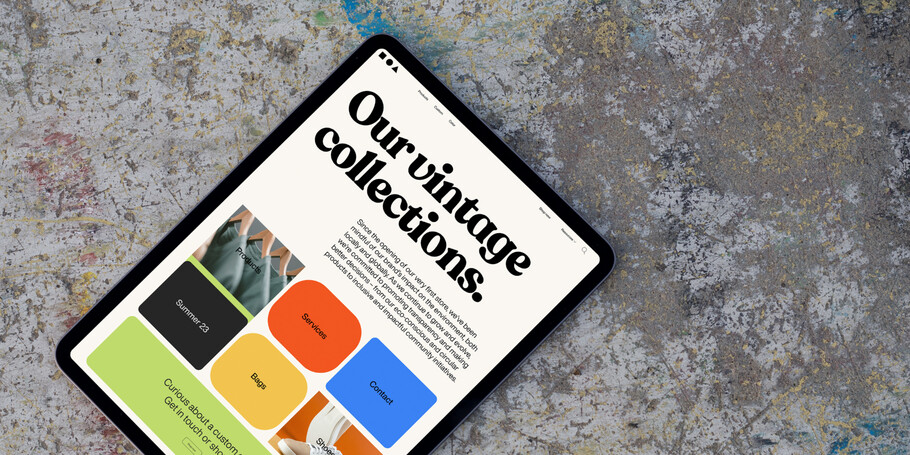
5 manières de renforcer la présence digitale de votre marque.
Vos polices de marque peuvent-elles passer en toute simplicité de votre magasin à un environnement Web ? Vos polices de caractères sont-elles lisibles dans une application ? Qu’en est-il des publicités ou des bannières numériques ?
Et des nouveaux environnements, tels que le métavers ? Qu’il s’agisse d’une simple page Web, d’une bannière publicitaire numérique, d’une application, d’une expérience en réalité virtuelle ou encore d’un nouveau jeu dans une arène virtuelle… Force est de constater qu’assurer la présence omni-canal et la transformation numérique d’une marque de manière cohérente sur toutes les plateformes, cela n’est pas une mince affaire.
De nos jours, les consommateurs naviguent à travers les écrans, passent du petit au grand et inversement. Les marques doivent impérativement suivre le mouvement. Et le choix des polices de caractères joue un rôle majeur. Si une marque veut maintenir un niveau de confiance élevé et créer une expérience client positive, il lui faut une présence cohérente sur tous ses points de contact.
La prochaine fois que vous vous retrouvez sur un projet de design pour le monde moderne, assurez-vous que vos polices de caractères sont à la hauteur de l’ère numérique. Utilisez cette check-list pratique pour ne rater aucun des éléments à vérifier.
1. La lisibilité
Si un designer trouve une police qui est parfaitement lisible sur un appareil, il faut savoir que celle-ci n’aura pas forcément la même clarté sur un autre. Agaçant ? Oui. Peut-on y remédier ? Tout à fait. Certaines pratiques peuvent entraîner un certain flou, une imprécision, voire une méfiance à l’égard d’une marque. C’est notamment le cas si vous utilisez une police native d’une application ou bien si vous ajustez l’espacement, caractère par caractère, jusqu’à ce que ce soit parfaitement lisible dans votre application de design. Les consommateurs doivent pouvoir lire facilement vos polices de caractères sur tous types de supports numériques, que ce soit sur une application, dans un jeu vidéo ou dans un paysage en réalité virtuelle. Il est donc essentiel de choisir une police de caractères conçue de manière experte pour fonctionner dans tous ces formats.
2. La vitesse de chargement
Aujourd’hui, c’est à travers un vaste paysage numérique que les marques interagissent avec leurs clients. L’aspect fonctionnel de leur typographie doit donc être pris en compte. Comment cette police de caractères gratuite, trouvée en ligne au gré du hasard, affecte-t-elle la vitesse de chargement de vos pages ? Si vous avez entre les mains de vieux fichiers de police, ce qui peut facilement être le cas, il est probable que cela ait un impact négatif.
Les clients n’ont pas le temps d’attendre. Dès que le temps de chargement est trop long, ils quittent votre page Web, votre nouvelle application ou votre jeu vidéo. Pour éviter cela, trouvez des polices provenant de sources qui veillent à optimiser les performances de leurs logiciels de polices. Si vos polices sont toujours récentes d’un point de vue technique, vous n’aurez jamais à vous soucier de ce qui se cache sous la surface.
3. La dynamique d’adaptation
Des grands titres d’un site Web au minuscule texte sur une montre connectée, l’utilisation de textes dynamiques – qui changent en fonction de la mise en page ou des paramètres – devrait être une évidence pour l’expérience numérique de toute marque. Nous avons déjà vu ce phénomène devenir courant dans le web 2.0, car de nombreux sites Web dynamiques passent facilement de l’ordinateur à la tablette, puis au mobile. Désormais, les marques devront réfléchir à la manière dont leurs polices de caractères apparaissent aussi dans des environnements plus collaboratifs et décentralisés, comme le web3, ainsi que dans les espaces de réalité augmentée et de réalité virtuelle.
Enfin, si un message ou un concept change, un designer (ou autre créatif de confiance) doit être en mesure de modifier rapidement le texte. C’est ce qui se passe en permanence sur les sites d’information, les mises à jour de jeux, ou même les points de vente qui se préparent pour une nouvelle saison. Dans l’espace en ligne, il n’y a plus grand-chose de statique à vrai dire. Une police de caractères dynamique offre l’agilité qui permet d’effectuer des changements efficaces, sans s’inquiéter d’un affichage illisible.
4. Les problèmes de rendu
Un autre conseil relatif à la fonctionnalité des polices ne doit pas être négligé : le rendu du texte. C’est un point compliqué, surtout lorsqu’il s’agit de développer des applications ou de créer d’autres ressources numériques, susceptibles de comporter des caractères nuancés. Les problèmes de rendu apparaissent lorsque les majuscules ne sont pas respectées, lorsque les caractères sont réorganisés, lorsqu’ils ont une forme ou une directivité incorrecte. Cela peut devenir particulièrement difficile avec des polices de caractères dans différentes langues. Les designers avisés savent reconnaître lorsque les problèmes de rendu, les polices pixellisées ou les mises en page peu sophistiquées sont des obstacles majeurs pour une marque. L’objectif est de choisir une police fiable avec un jeu complet de caractères et des scripts intégrés, dont le rendu ne pose aucun problème.
5. Le branding
Jusqu’ici, nous avons abordé les points fonctionnels et créatifs qui permettent d’obtenir un texte clair, lisible et rapide à charger sur tous les appareils. En fin de compte, tout cela se résume à la représentation de la marque. Lorsqu’une police disponible pour l’impression n’est pas optimisée pour le web, les designers doivent faire un choix difficile avec une police Web qui n’est pas tout à fait à la hauteur. Parfois, ils peuvent s’en sortir. Parfois, c’est un véritable gâchis. Quand une expérience de marque est incohérente entre le physique et le numérique, cela crée une sorte de phénomène de la vallée de l’étrange dans l’esprit du consommateur : elle suscite inconsciemment (parfois consciemment) de la méfiance, un sentiment de moindre empathie ou de détachement à l’égard de la marque.
Les marques peuvent éviter ce problème en choisissant une police de caractères qui fonctionne de manière identique dans les environnements physiques et numériques. D’autant plus quand on sait que nous plongeons la tête la première dans un avenir de réalité mixte (le métavers, nous te voyons). Ce qu’il faut en retenir ? En tant que designer, votre tâche consiste à faire en sorte qu’il n’y ait pas de rupture dans l’expérience de la marque. Les polices de caractères jouent un rôle essentiel à cet égard.
Avec une solution basée sur le cloud comme celle-ci, vous pouvez jeter cette check-list par la fenêtre. (Enfin, attendez peut-être un peu.) En tout cas, c’est un programme qui ressemble bel et bien à un vœu qui se réalise. Et d’ici-là, voici la version condensée de ce qu’il faut vérifier en matière de polices de caractères. Pour en savoir plus sur Monotype Fonts, consultez le site Monotype.com.
Check-list pour la typographie des produits numériques
- Lisible
- Chargement instantané
- Dynamique
- Pixellisation parfaite
- Cohérente avec la marque